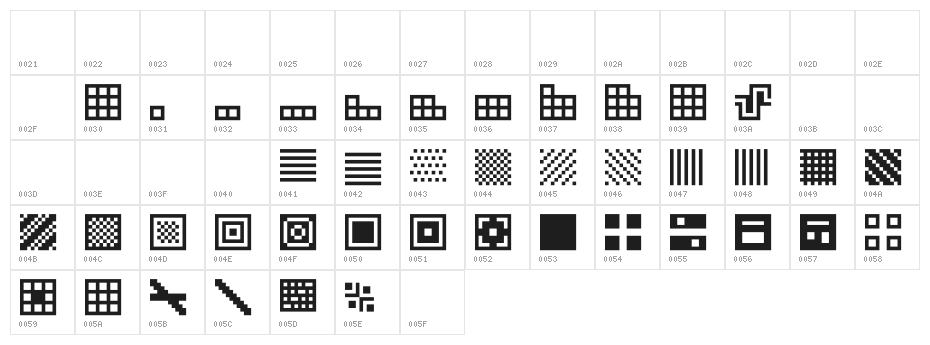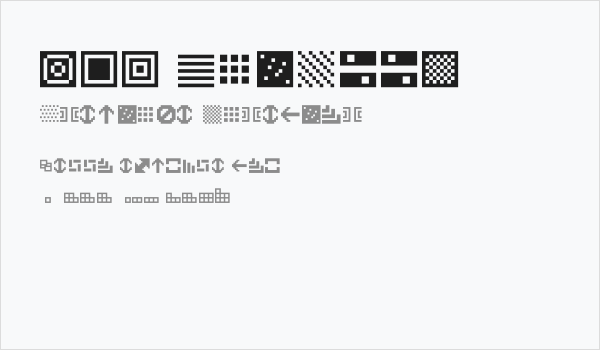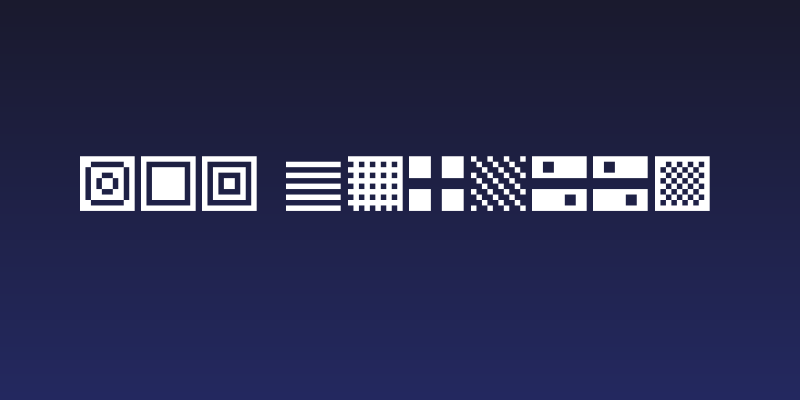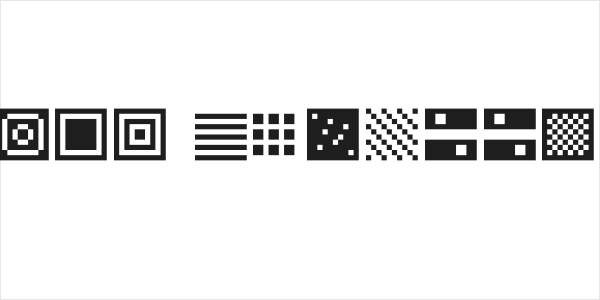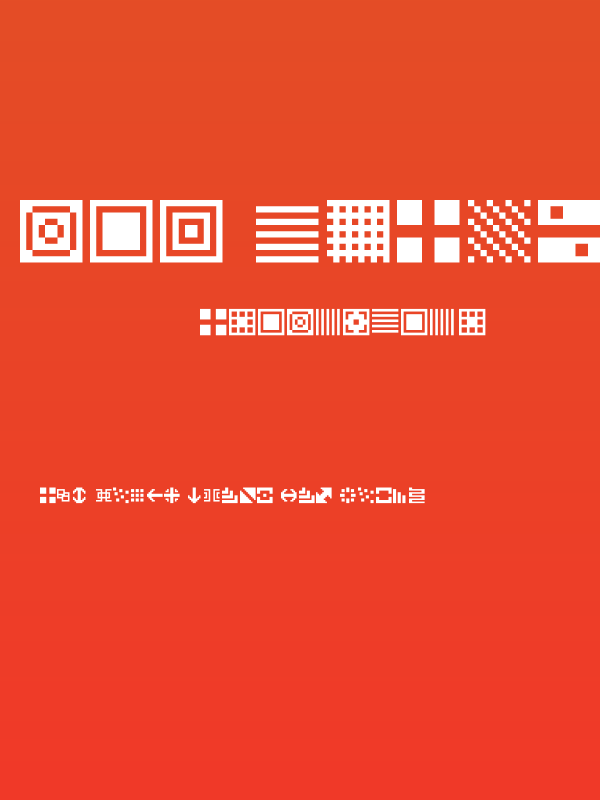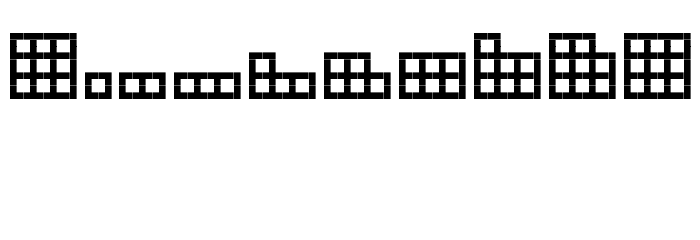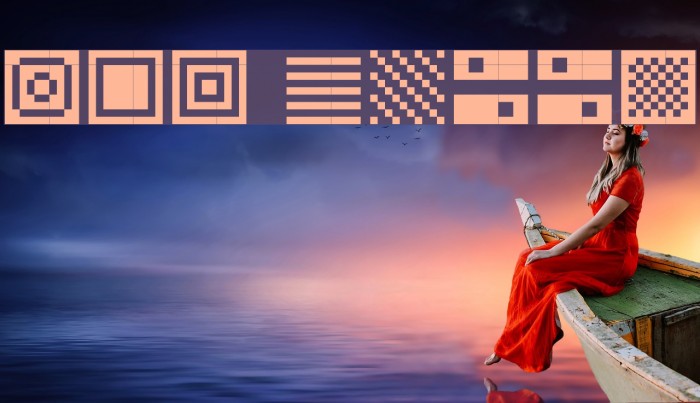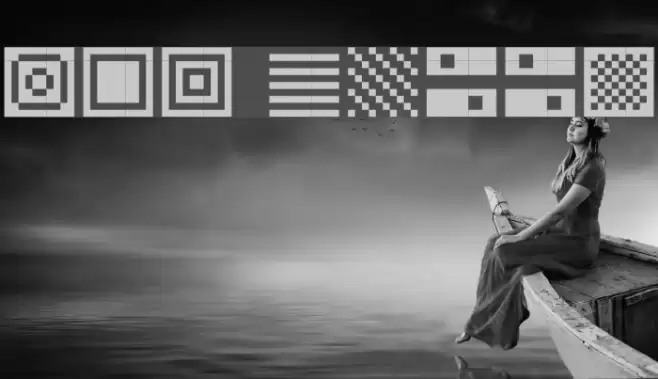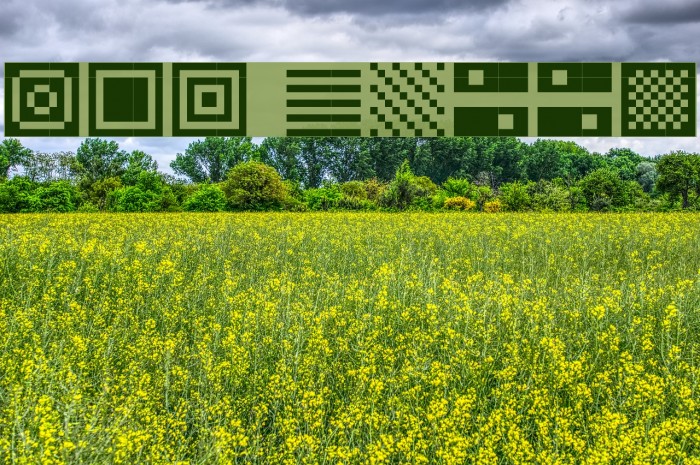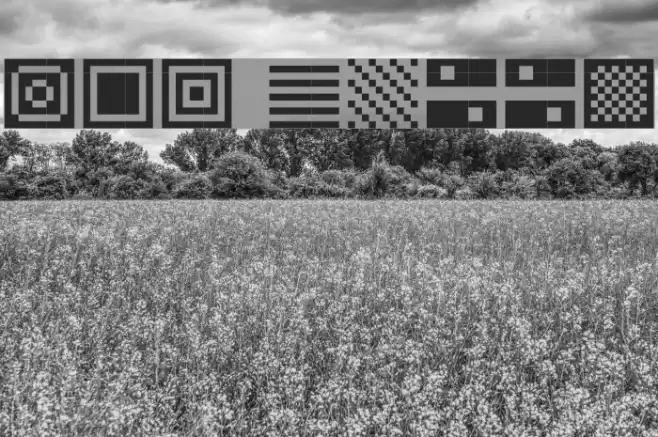
OPN BitFUUL Font
| Gesamtstil | Retro, Digital, Abstract |
| Anwendungsfall | Logos, Digital Art, Themed Graphics |
| Vorgeschlagene Projekte | Ideal for digital art projects, retro-themed designs, video game graphics, or any creative work that embraces a pixel art style. |